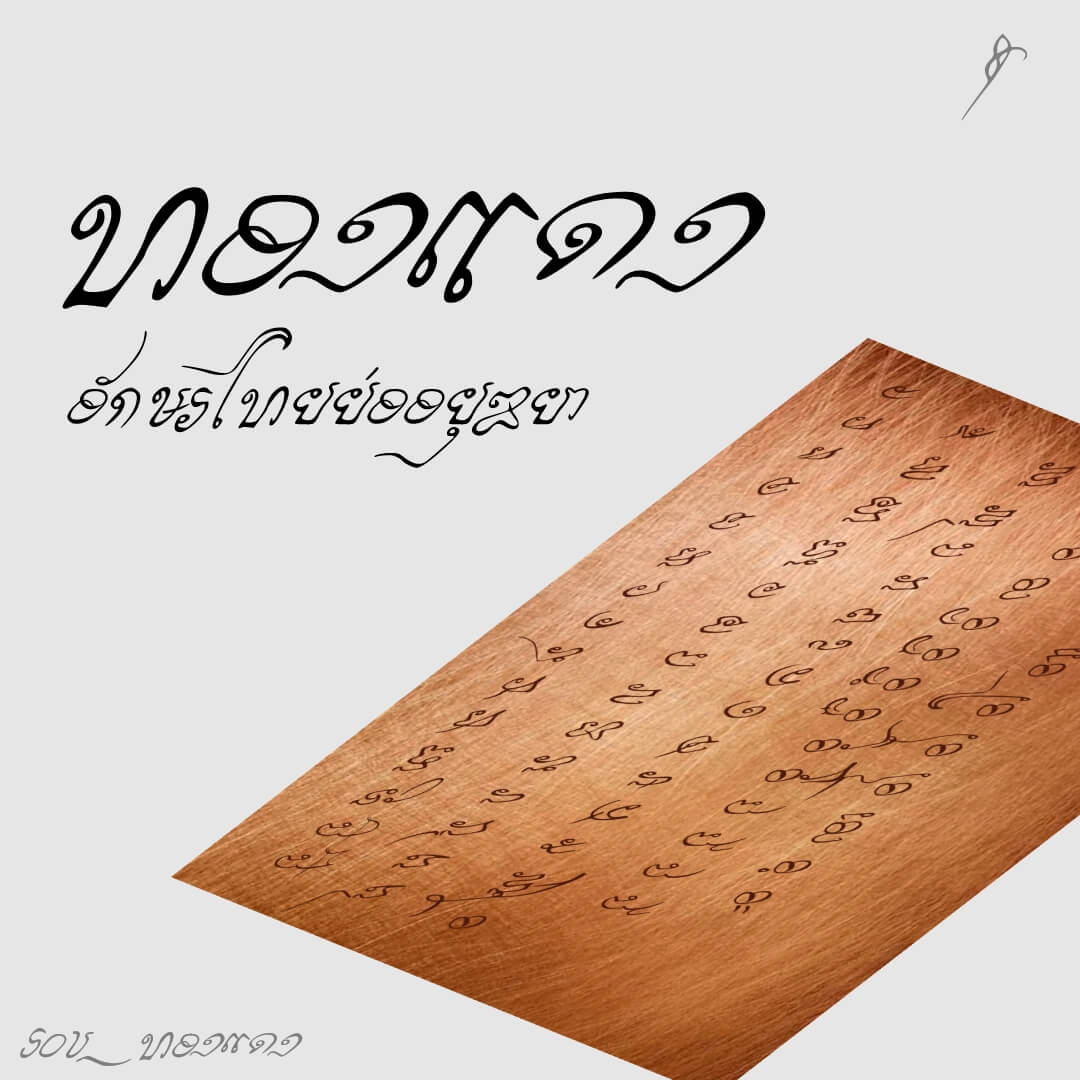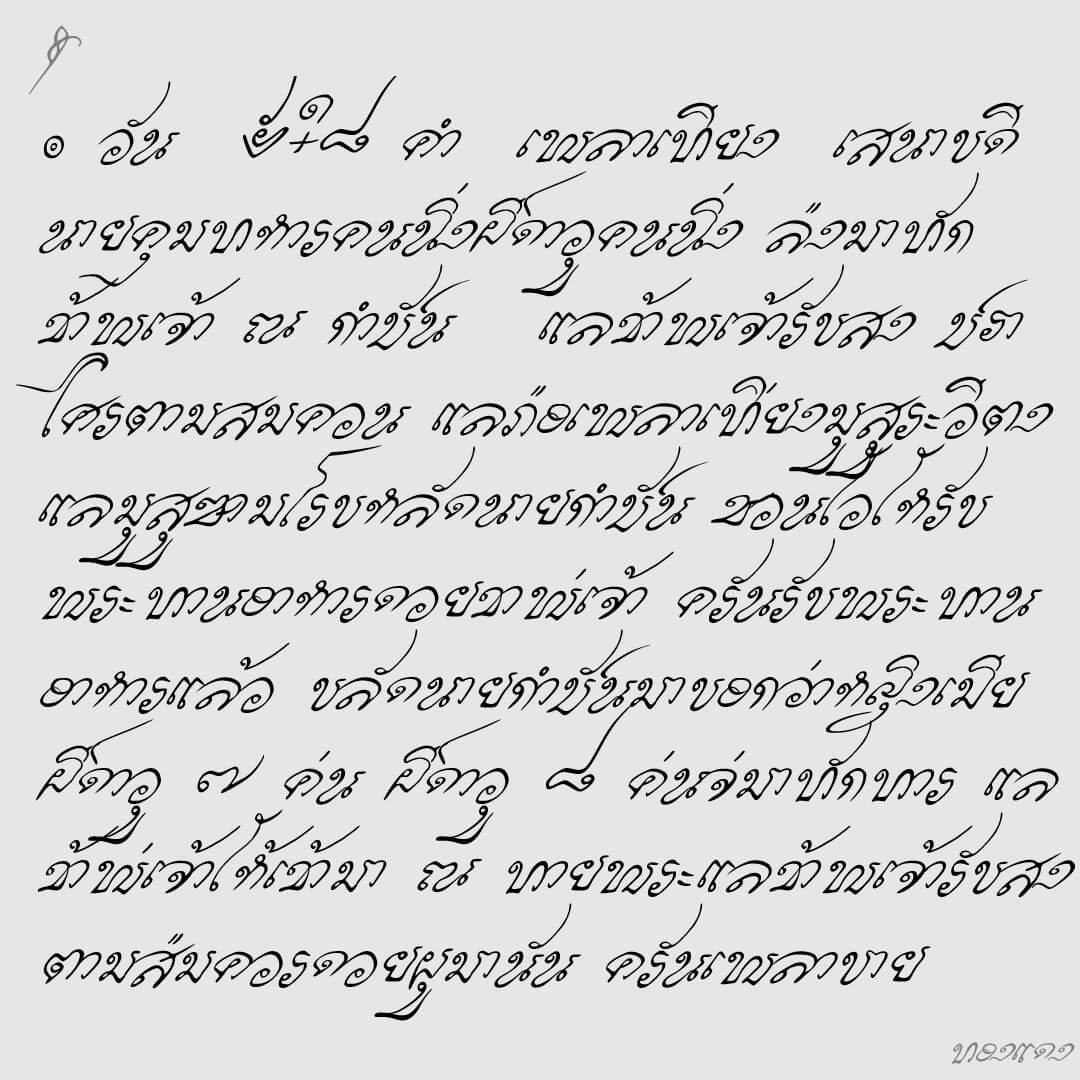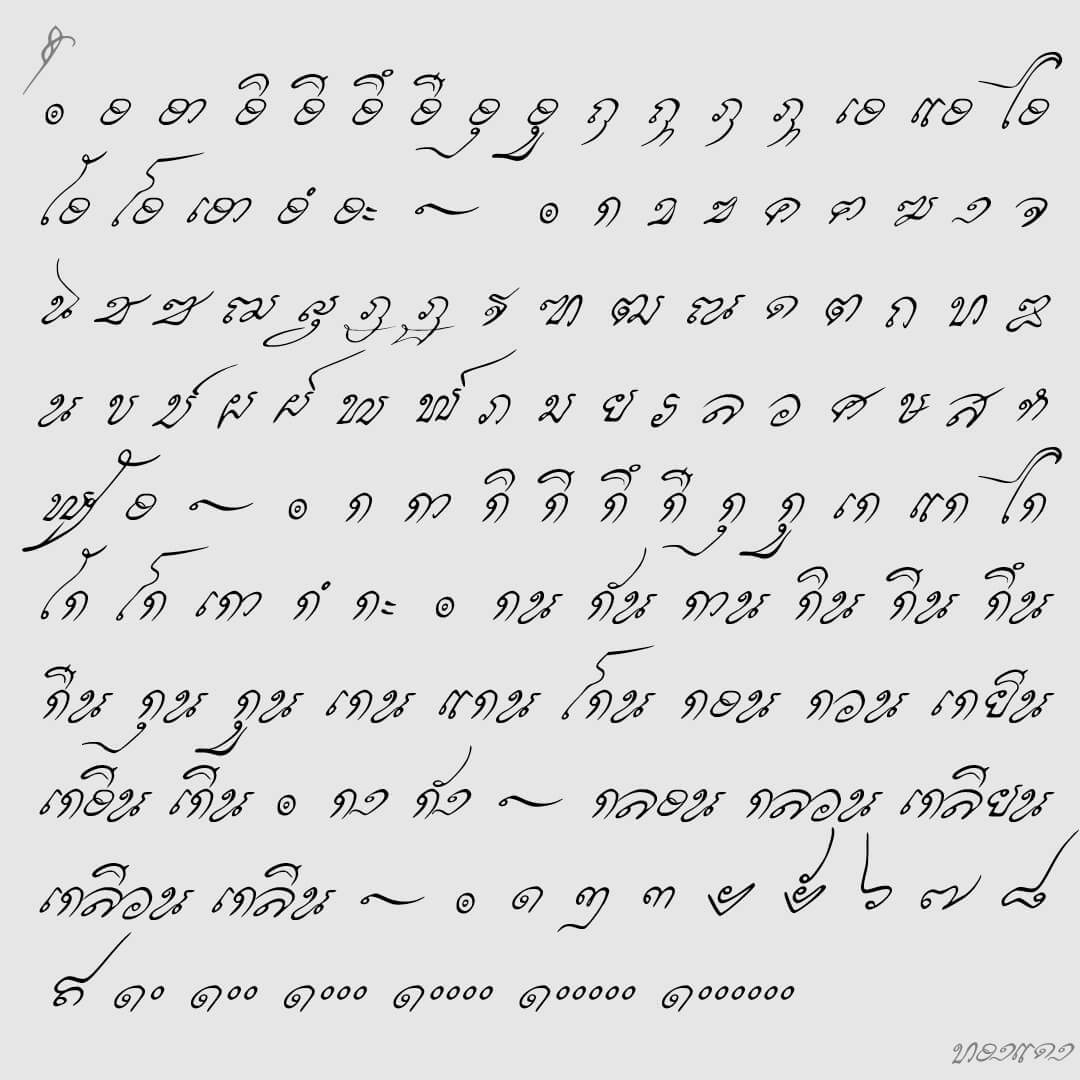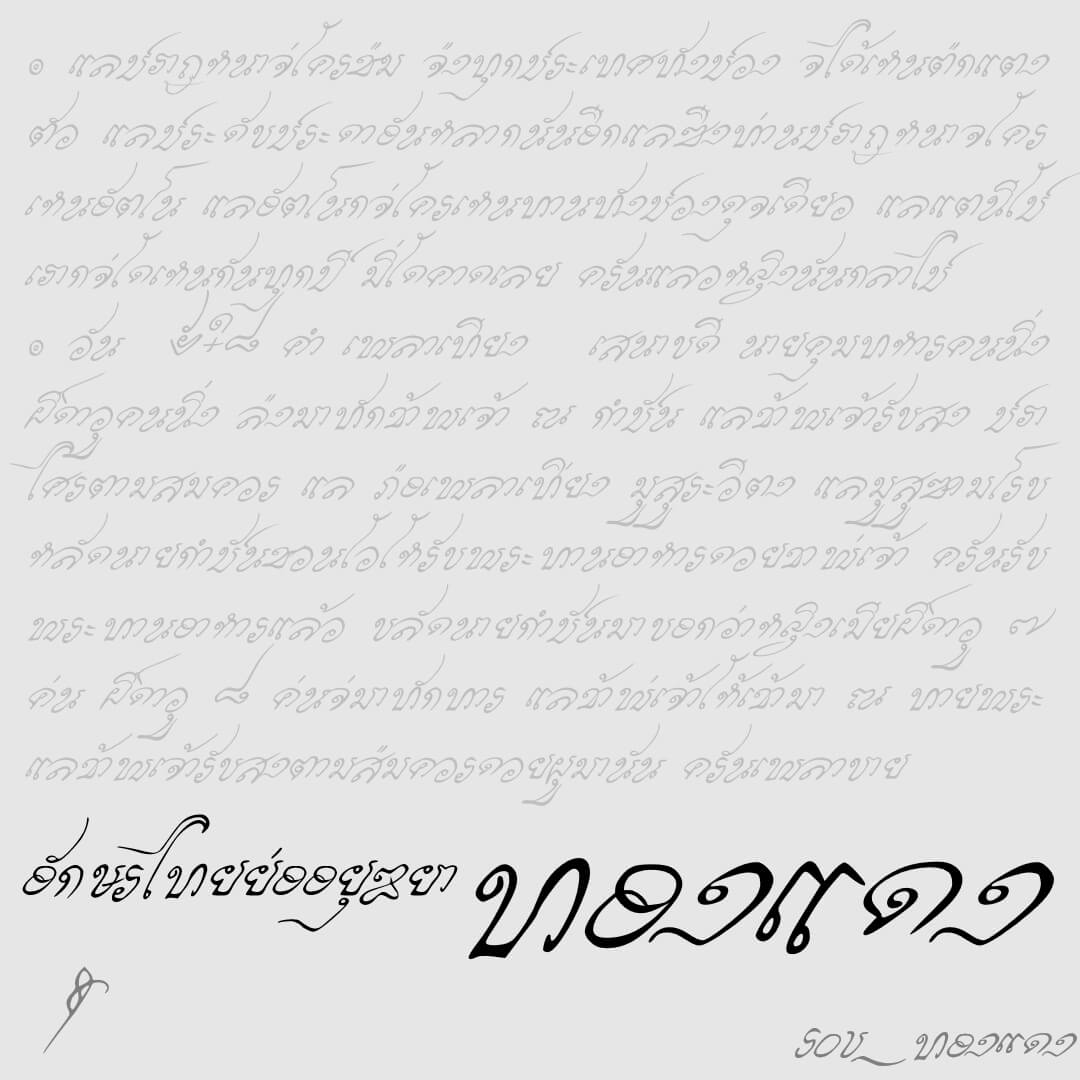
ทองแดง (SOV_TongDang)
ฟอนต์ทองแดง – เป็นฟอนต์ที่จินตนาการว่าถ้าฝรั่งยุโรปที่เข้ามาในแผ่นดินสมเด็จพระนารายณ์ เขียนอักษรไทยอยุธยาหน้าตาน่าจะประมาณนี้ (ถ้าผู้รู้มีคำแนะนำเพิ่มเติมบอกได้นะครับ)
หมายเหตุ :
รูปแบบตัวอักษรหลักๆ จากภาพพิมพ์ทองแดง ‘The SYAM Alphabett.’ โดย Michael Burghers เมื่อ 300 กว่าปีที่แล้ว โดยอักษรดังกล่าว อ้างอิงมาจาก อักษรที่เขียนด้วยลายมือถวายพระเจ้าชาร์ลส์ที่ 2 ในปี ค.ศ.1684
แต่ในแบบดังกล่าวยังมีอักษรไม่ครบถ้วนในยุคนั้น ผมจึงได้เพิ่มอักษรเข้าไป โดยอิงจาก ‘Trois Alphabeth Siamois.’ โดย La Loubere (จดหมายเหตุลาลูแบร์) พิมพ์ปี ค.ศ. 1691, เอกสารประชุมจดหมายเหตุออกพระวิสูทสุนทร(โกษาปาน) พ.ศ. ๒๒๓๑ (ประมาณ ค.ศ. 1688) และนิราศต้นทางฝรงงเสษ พ.ศ. ๒๒๒๙ (ประมาณ ค.ศ. 1686)
ส่วนในวรรค ฏ ที่ไม่พบนั้น ผมจินตนาการรูปแบบอักษรขึ้นมาเองเพื่อให้ครบถ้วนตามยุคสมัย โดยอิงจากจารึกในปี พ.ศ.ใกล้เคียงกัน